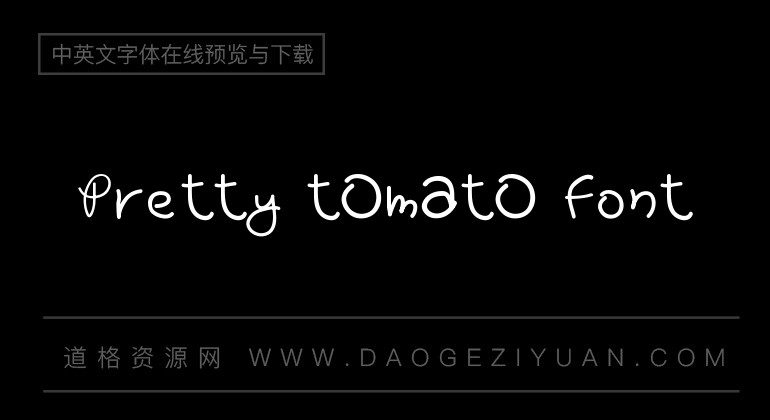
Pretty tOmAtO Font 是一种手写风格的字体,具有轻快、自然、可爱的特点。它是由日本设计师 Haruka Matsukura 创造的,旨在呈现出手写字体的温暖和个性化。该字体的字形有些类似于日本的假名,但同时也具有拉丁字母的特点,因此非常适合用于设计带有东方元素的海报、广告、包装设计等。此外,该字体还有不同的粗细和变体可供选择,方便设计师根据需要进行调整和优化。内容介绍
Pretty tOmAtO Font是一款非常不错的手写艺术字体,具有很好的视觉感,适合于文化类的宣传设计、商业类品牌的广告和产品包装设计以及个性化文字排版等较多场景。